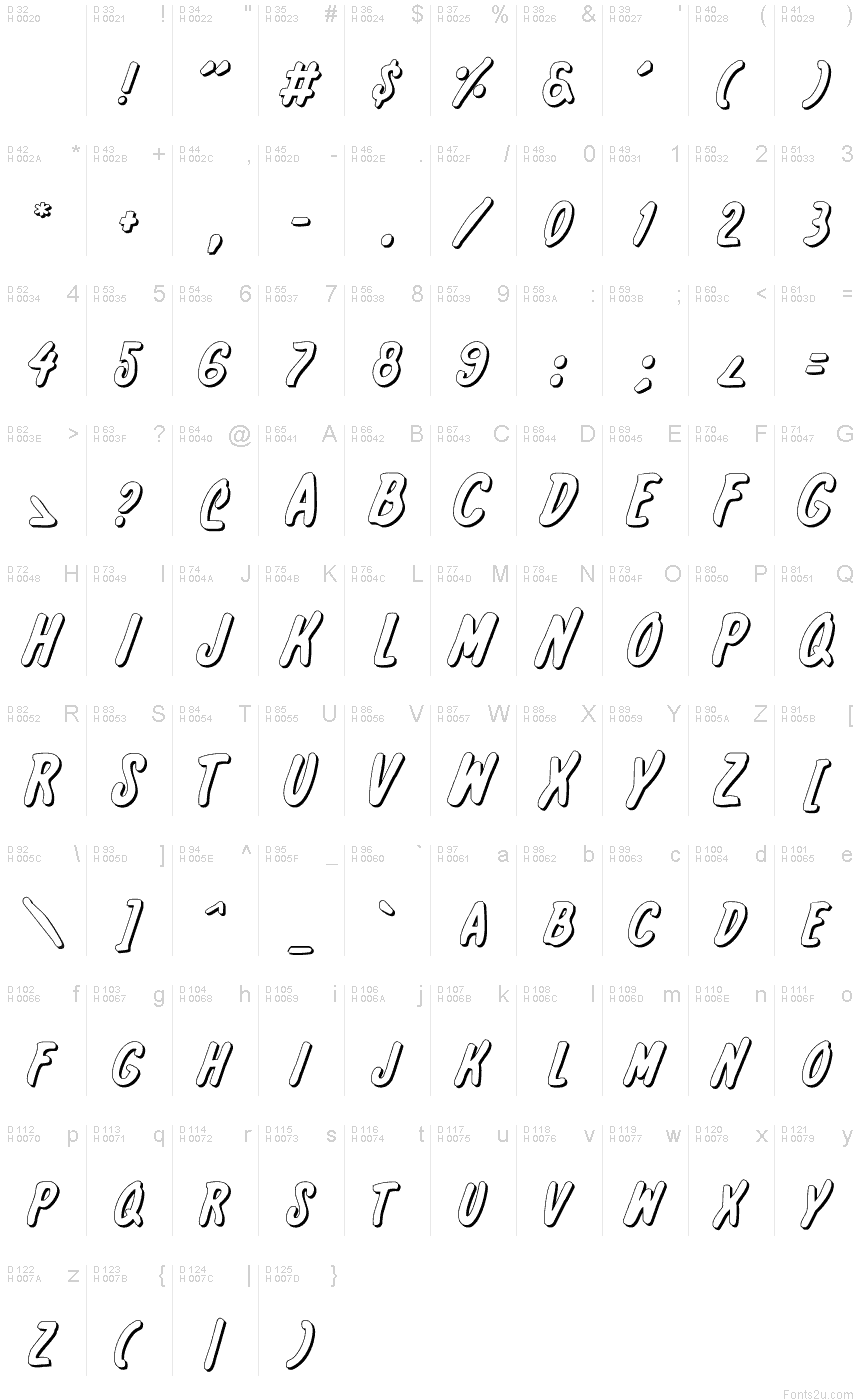
International Super Hero Out di Iconian Fonts è un carattere display gratuito in stile fumetto che urla forte come una nuvoletta in una scena d'azione. Le sue lettere arrotondate e dinamiche si inclinano in avanti con un marcato bordo nero, dando a ogni parola quell'energia esplosiva da supereroe. Gli interni vuoti mantengono il design leggero e arioso, così anche i titoli più grandi e rumorosi non risultano mai pesanti o compressi.
Con International Super Hero Out, i tuoi titoli attireranno immediatamente l'attenzione su copertine di fumetti, libri per bambini, loghi di giochi, miniature di YouTube, confezioni di giocattoli e poster giocosi. Il ritmo vivace e le curve corpose si leggono chiaramente anche nelle grandi dimensioni, persino su sfondi complessi. Questo font gratuito si abbina perfettamente a un carattere sans serif pulito per il corpo del testo: lascia che International Super Hero Out si occupi dell'azione, mentre il testo di supporto mantiene stabilità e chiarezza.
Mappa dei caratteri di International Super Hero Out